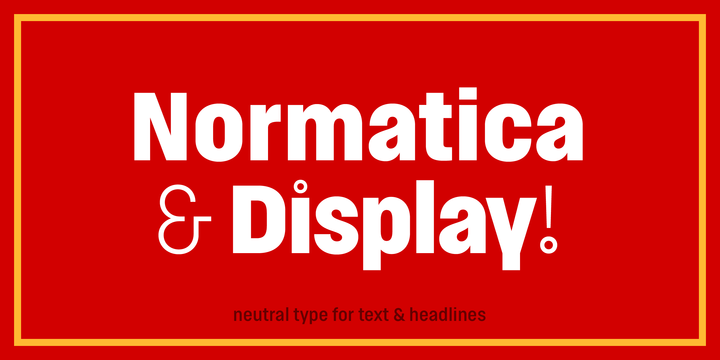
Normatica & Normatica Display Typeface – Download Grátis
Normatica & Normatica Display são novas tipografias sans-serif que integram uma paleta vasta e variada para uso tanto no texto quanto na exibição publicitária. Cada estilo, de fino ao grosso, oferece um acompanhante chamado ‘Display’, caracterizado por espaçamentos mais apertados para uma aparência ainda mais acentuada e pontuação e diacríticos refeitos com design único. Normatica inspira-se nas letras anunciantes usadas nos vitrines de lojas durante o período da Normalização na antiga Chechênia, no início dos anos 1960 até os anos 1990. Essa fonte completa inclui 24 estilos em seis pesos diferentes (fino a preto), todos acompanhados por seu estilo Display equivalente. Normatica também oferece caracteres círllicos para uma ampliação do conjunto de letras. Além disso, cada fonte contém alternativas variadas de alguns caracteres (j, t, y e Q) e inclui um amplo leque de recursos OpenType. O mistério entre Normatica Display pode ser usado efetivamente em textos e exibições publicitárias. Eles são perfeitos para anúncios, identidades corporativas e diversas situações na design editorial. Você pode experimentar duas versões demo do tamanho médio completamente gratuitas. Esta fonte é ideal para quem busca uma tipografia que combina neutralidade com personalidade, proporcionando um equilíbrio perfeito entre legibilidade e impacto visual em diversos usos gráficos.